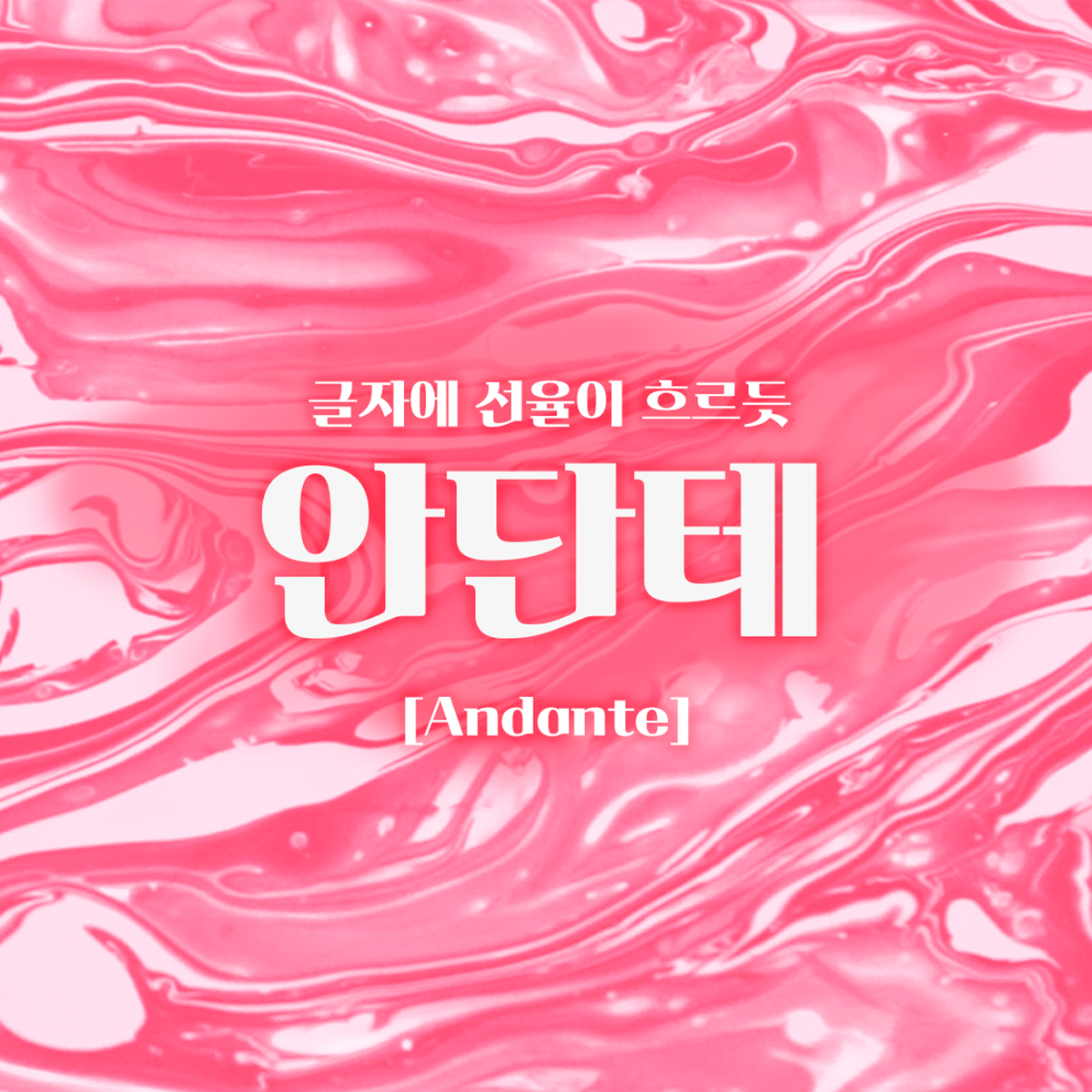
Sandoll 안단테
분류 Serif,디스플레이
제목용출판서정적
산돌 안단테는 리듬감 있는 형태와 수수한 디자인을 통해 클래식한 느낌을 준 폰트이다.
느리게 연주하기라는 뜻의 음악용어 Andante에서 모티브를 얻었으며, 영문폰트 Bodoni를 연상시키는 콘트라스트와 세리프의 표현으로 딱딱한 고딕에서 우아하고 여성적인 느낌을 살렸다.